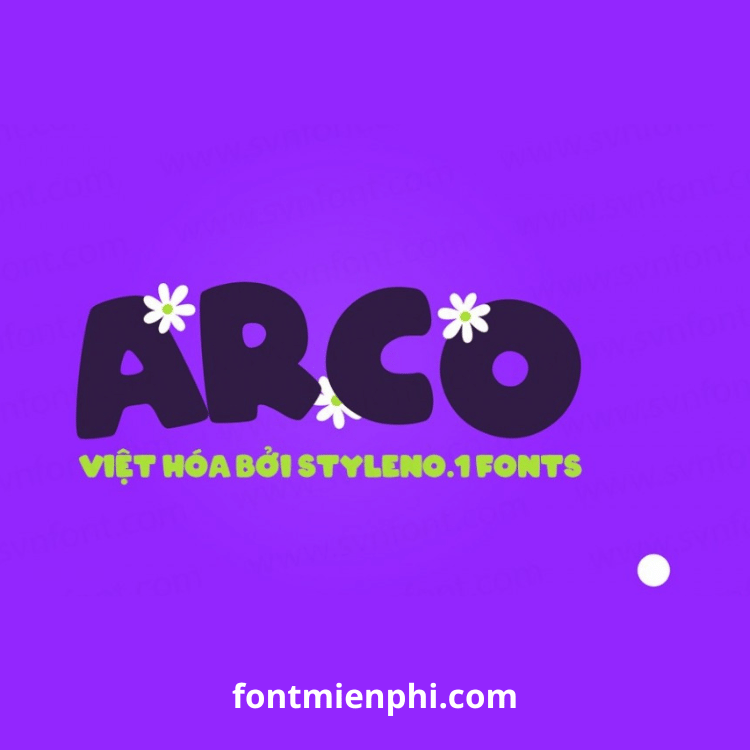
Việt hóa font SVN ARCO Typography
Mô tả font SVN ARCO Typography (Việt hóa):
SVN ARCO Typography là font chữ display mạnh mẽ, phong cách hiện đại với các nét vuông vức, góc cạnh. Phiên bản Việt hóa hỗ trợ đầy đủ dấu tiếng Việt, phù hợp thiết kế ấn tượng như poster, logo, banner, hoặc các dự án cần sự cá tính.
Ứng dụng thiết kế – Việt hóa font SVN ARCO Typography :
- Poster quảng cáo, bìa sách/tạp chí
- Logo thương hiệu, bao bì sản phẩm
- Trình chiếu PowerPoint, hình ảnh social media
- Thiết kế áo thun, phụ kiện thời trang
Font phù hợp với phong cách urban, thể thao hoặc công nghệ.